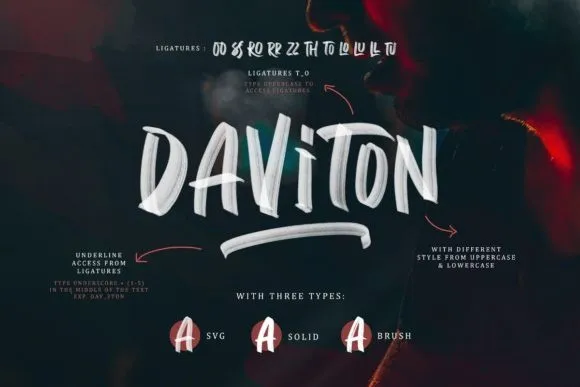
Daviton Font – Download Grátis
A fonte ‘Daviton Font’ é um belo tipo brush uppercase para ambientes de exibição moderna. Desenvolvida pelo talentoso designer Saridezra, ela está disponível em três estilos: brush, solid e uma versão SVG. Esta font permite criar escritas fidedignas que parecem tão reais quanto se fosse escrever a mão. Seu uso é extremamente ampliado, desde promoções até designs de produtos ou anúncios digitais, oferecendo inúmeras possibilidades criativas. Com sua versatilidade e beleza única, a ‘Daviton Font’ é uma escolha excelente para quem procura um tipo brush que seja tanto original quanto funcional, tornando-o perfeito para o seu próximo projeto visual.